第九届“方正奖”字体设计大赛在京颁奖
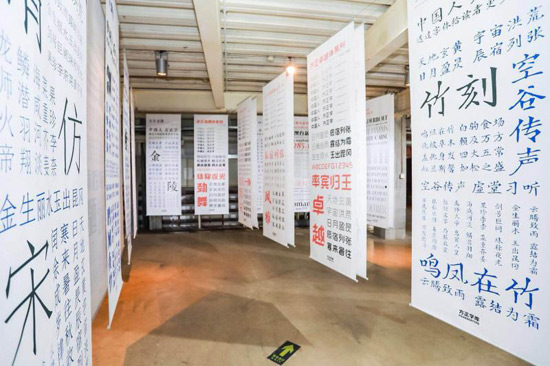
人民网北京4月4日电(记者葛亮亮)第九届“方正奖”字体设计大赛颁奖礼,日前在北京举行。同时,“字道2018”系列巡展也正式拉开帷幕。第九届“方正奖”字体设计大赛由中国文字字体设计与研究中心、北京北大方正电子有限公司、中央美术学院联合主办。
“方正奖”字体设计大赛自2017年3月启动以来,共收到3000多件作品,经过评委的严格审核,字体类别奖、评审委员奖、最佳人气奖、优秀指导老师奖等四档奖项全部揭晓。
本届字体设计大赛更注重字体设计实用性、规范性与艺术性的平衡,以“规范、实用”为指导,强调“字体为用而设计”,有创意、接地气。另外,大赛重新调整了竞赛类别,分为“中文专业组”“中文学生组”“拉丁文组”,让专业人士与在校学生分组竞技,强化了竞赛公平性,也让更多有天赋、有潜力的学生脱颖而出。“拉丁文字体设计”从第八届大赛开始成为大赛的一个固定单元,这让赛事更加开放、包容,也更具国际视野。
“方正奖”字体设计大赛是中国第一个面向字体行业的设计类赛事,也是字体设计领域内影响力最广、参与人数最多的专业赛事。从2001年第一届设计大赛举办至今,已举办九届大赛,总计有数万名字体爱好者、设计师参加。大赛有力推动了中文字体设计的创新,许多优秀的获奖作品被开发成为字库并服务于人们的生活,同时也为行业挖掘、培养了一大批出色的设计人才。如今活跃在设计界的众多知名设计师,都曾经参加过字体大赛。
“字道2018”巡展同期正式拉开帷幕,这是“字道”系列巡展第三次开展。本次展览包括两大看点:第63届纽约字体指导俱乐部全球巡展和“方正奖”字体设计大赛作品展。一中一西,荟聚最出色的创意作品,为公众呈现东西方文字迥然相异的风韵与魅力。
其中,第63届纽约字体指导俱乐部全球巡展展出的是2017年度纽约TDC字体设计竞赛获奖作品。纽约TDC字体设计竞赛是全世界最重要的平面设计竞赛之一,专业度极高,在业界享有盛誉。“方正奖”字体设计大赛作品展,不仅展示第九届“方正奖”字体设计大赛的优秀获奖作品,也展示了方正字库的精品字体,体现了中国字体设计的目前最高水准。